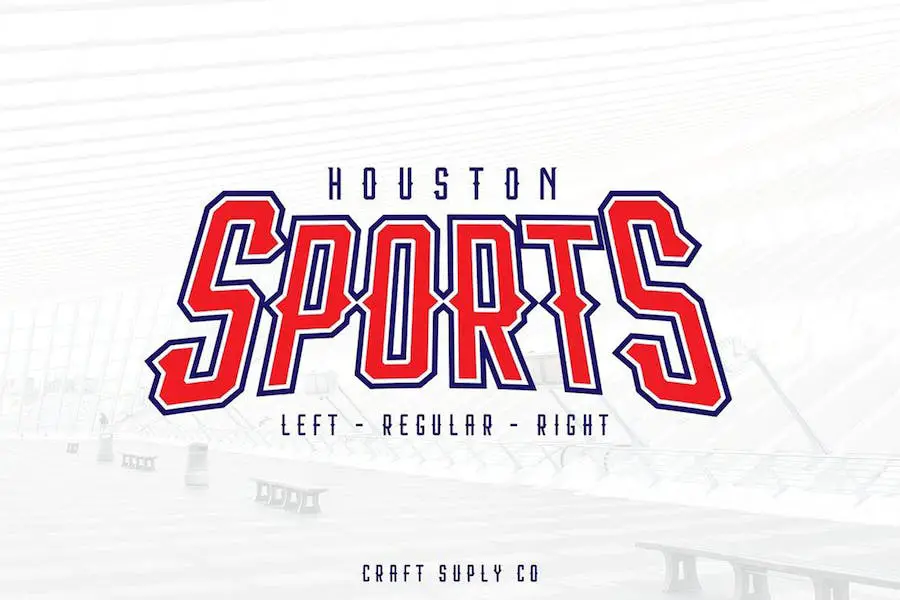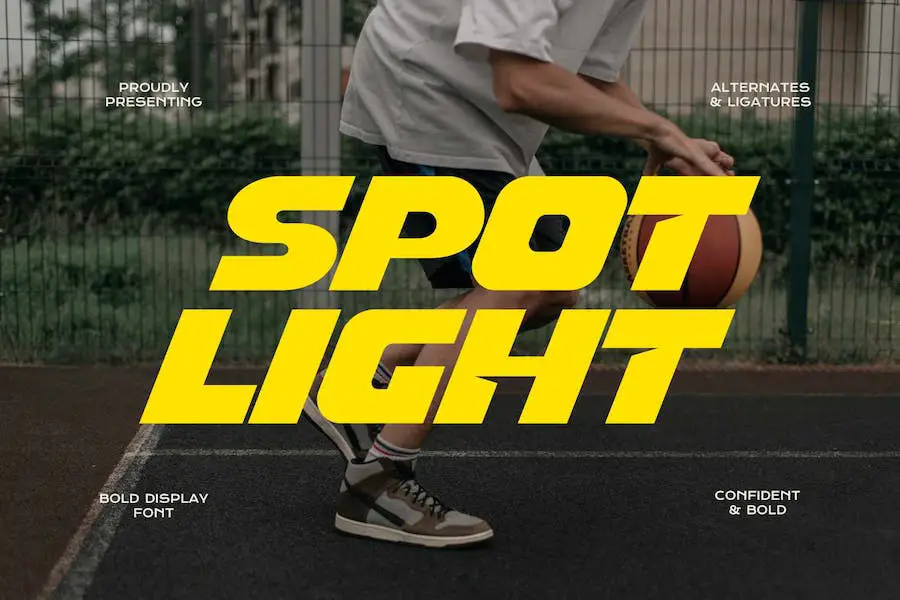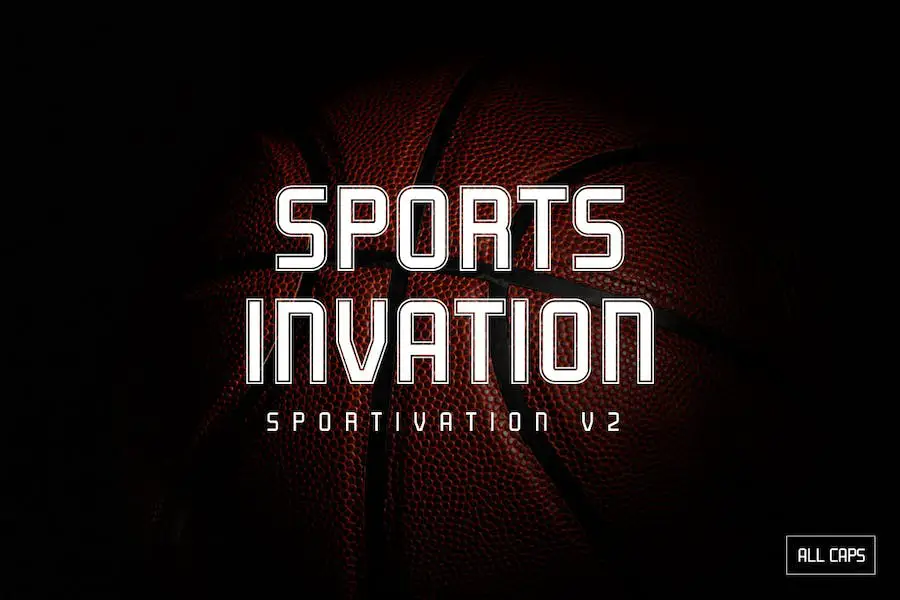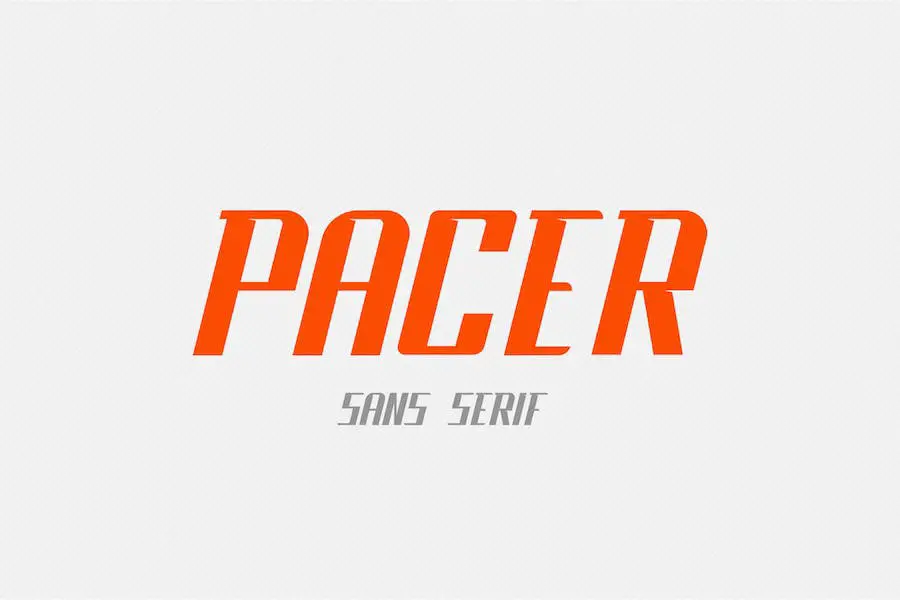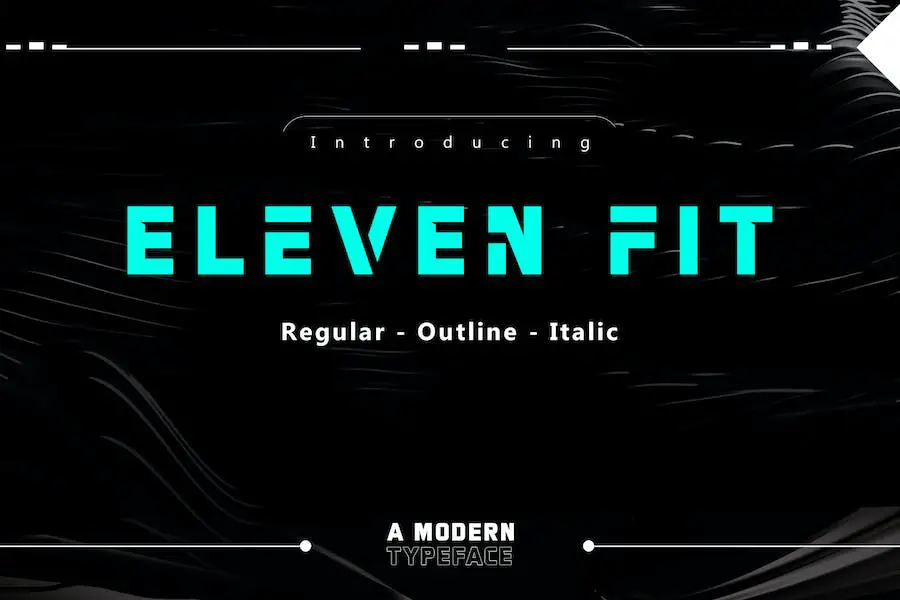
38 Font Olahraga Terbaik 2023 (Gratis & Premium)
Diterbitkan: 2023-07-16Apakah Anda seorang desainer grafis yang ingin membawa proyek Anda ke level selanjutnya? Apakah Anda lelah menggunakan font lama yang sama dan ingin menemukan sesuatu yang unik dan menarik? Nah, Anda beruntung!
Dalam posting blog ini, kami akan mengeksplorasi 38 font olahraga terbaik yang akan membantu meningkatkan permainan desain Anda dan membuat karya Anda menonjol.
Sekarang, Anda mungkin bertanya-tanya, “Mengapa font olahraga?” Nah, font olahraga adalah pilihan populer di kalangan desainer karena menghadirkan nuansa yang kuat dan dinamis pada desain apa pun.
Apakah Anda sedang mengerjakan proyek yang berhubungan dengan olahraga atau hanya ingin menambah energi dan kegembiraan pada desain Anda, font ini pasti akan berhasil.
Pada artikel ini, kami akan menampilkan berbagai macam font olahraga, mulai dari yang tebal dan atletis hingga ramping dan modern. Setiap font telah dipilih dengan cermat berdasarkan keunikan, keserbagunaan, dan kemampuannya untuk memberikan dampak visual.
Jadi apakah Anda sedang mendesain logo olahraga, poster, atau bahkan situs web, font-font ini akan membantu Anda membuat desain menakjubkan yang menangkap semangat olahraga.
Jadi, tanpa basa-basi lagi, mari selami dunia font olahraga dan temukan font terbaik yang akan membawa proyek desain Anda ke ketinggian baru.
Font Olahraga Premium Terbaik
Ingin membawa desain olahraga Anda ke level selanjutnya? Tidak terlihat lagi dari pilihan font premium terbaik kami yang dirancang khusus untuk proyek bertema olahraga. Bersiaplah untuk menyempurnakan desain Anda dengan tipografi terbaik ini yang pasti akan mengesankan audiens Anda.
Selami dan temukan font yang sempurna untuk proyek olahraga Anda berikutnya!
Olahraga Gimnasium
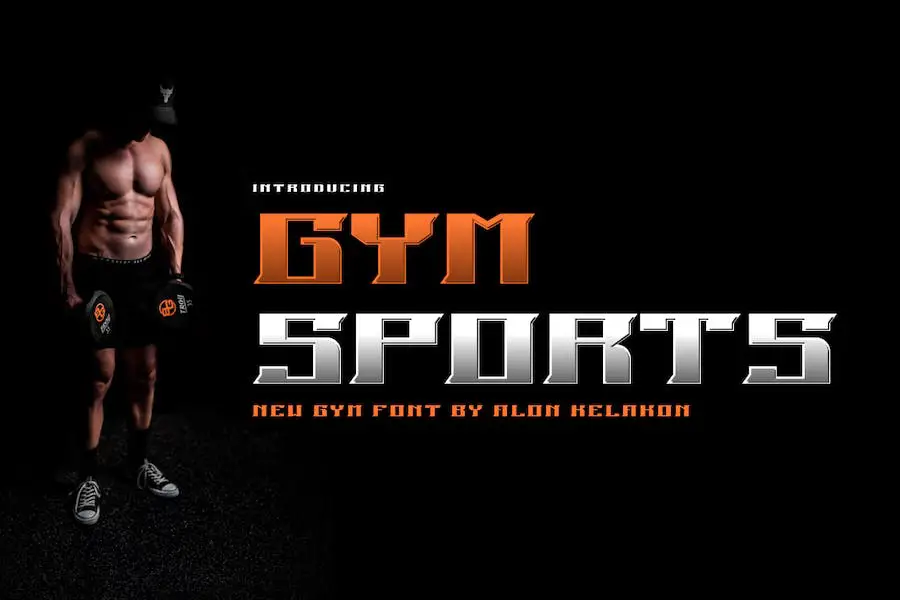
Gym Sports Font adalah jenis huruf unik dan serbaguna yang dapat meningkatkan proyek desain grafis Anda. Baik Anda membuat label, desain pakaian, poster film, atau logo, font ini siap membantu Anda.
Dengan tampilannya yang stylish dan dinamis, sempurna untuk menyampaikan rasa atletis dan energik. Gunakan Gym Sports Font untuk menambahkan sentuhan profesional dan menarik pada desain Anda.
Gym Sports Font juga merupakan pilihan tepat untuk judul film dan sampul album. Penampilannya yang berani dan dinamis menambahkan elemen yang menawan dan menarik secara visual pada produksi sinematik atau musik apa pun.
Grasher
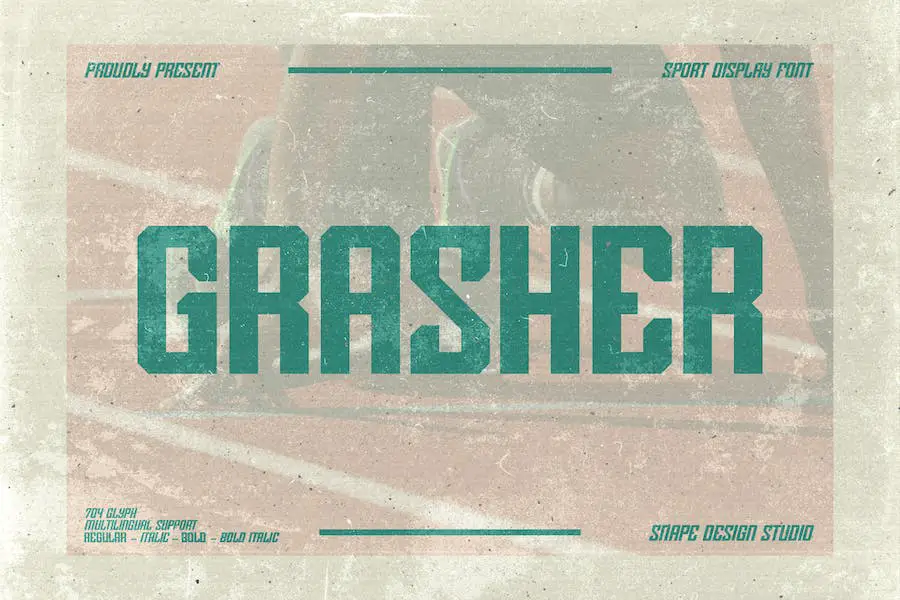
Grasher adalah font olahraga yang sempurna untuk logo, branding, dan desain atletik. Dengan rasa yang berani dan kuat, itu langsung menarik perhatian dan menambahkan sentuhan hidup pada proyek apa pun.
Baik Anda mendesain untuk tim olahraga, membuat poster atau sampul buku, atau bahkan mengerjakan film atau dokumenter, Grasher akan membuat desain Anda menonjol dengan gayanya yang unik.
Jika Anda penggemar estetika olahraga vintage, Grasher adalah font untuk Anda. Desainnya menangkap esensi tipografi olahraga klasik, memberikan desain Anda nuansa nostalgia dan autentik.
Ini sempurna untuk membuat logo, branding, atau desain yang terinspirasi gaya vintage yang membutuhkan sentuhan pesona olahraga jadul.
Berani
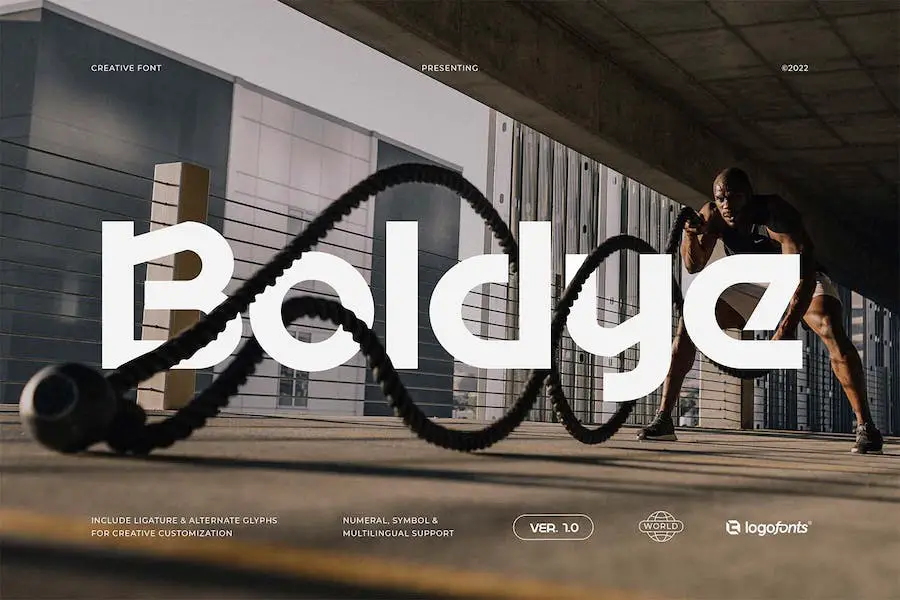
Memperkenalkan Boldye, font olahraga yang mengambil inspirasi dari logo ikonik Reebok dan gaya tipografi olahraga. Font ini adalah tentang kekuatan dan keserbagunaan, dengan kurva tebal dan tepi tajam yang memberikan desain Anda tampilan yang kuat dan dinamis.
Salah satu fitur menonjol dari Boldye adalah berbagai huruf dan pengikat alternatif uniknya, yang dapat diakses melalui fitur Open Type-nya.
Ini memungkinkan Anda dengan mudah membuat jenis logo Anda sendiri dan menambahkan sentuhan pribadi pada desain Anda. Dengan font ini, Anda benar-benar dapat melepaskan kreativitas Anda dan mewujudkan ide-ide Anda.
Olah Raga
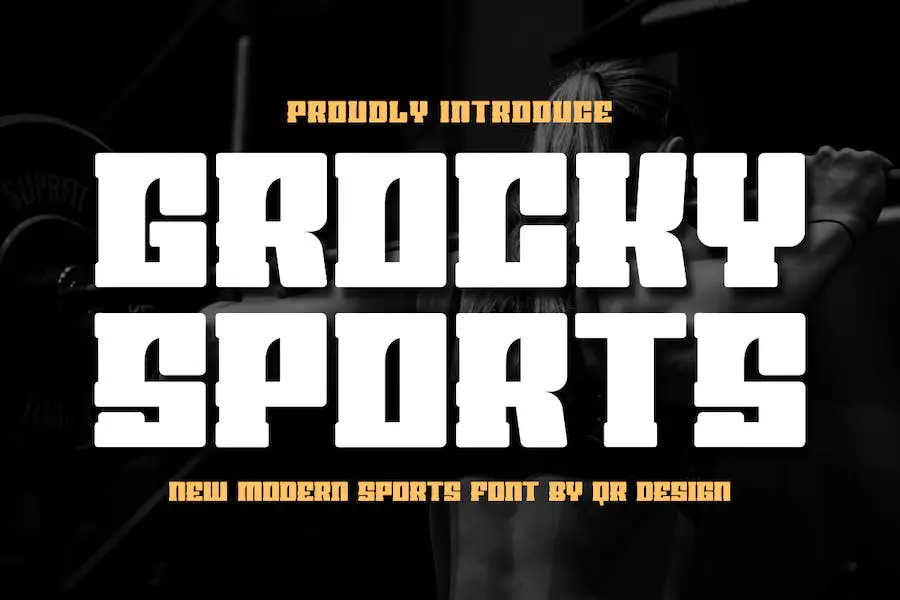
Grocky Sports adalah font olahraga unik yang sempurna untuk desainer grafis yang ingin menyempurnakan proyek mereka. Font ini serbaguna dan dapat digunakan untuk berbagai keperluan desain seperti pelabelan, pakaian, adegan film, poster, sampul album, logo, dan lainnya.
Desainnya yang modern dan bergaya akan menambah sentuhan profesional pada proyek apa pun. Dengan Grocky Sports, Anda dapat dengan mudah membuat desain menarik yang akan membuat klien Anda terkesan dan memikat audiens Anda.
Jadi mengapa puas dengan font biasa ketika Anda dapat meningkatkan desain Anda dengan font olahraga yang luar biasa ini? Coba Grocky Sports hari ini dan bawa proyek Anda ke level selanjutnya.
Heisman
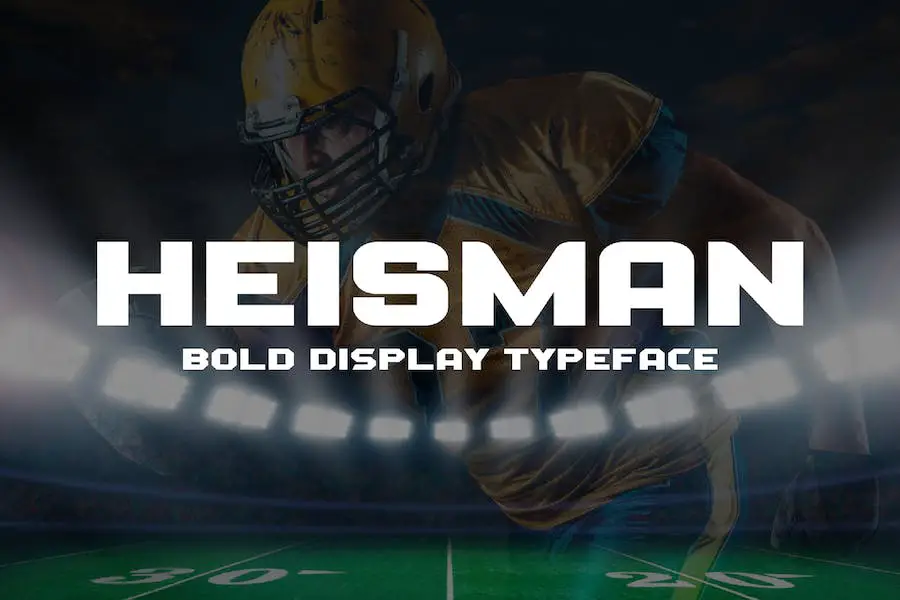
Heisman adalah pilihan utama bagi mereka yang berada di dunia desain grafis yang mencari font yang akan membawa proyek olahraga mereka ke level berikutnya.
Font huruf kapital semua ini menonjolkan kumpulan karakter huruf kecil dan besar yang unik, menjadikannya sempurna untuk iklan, tajuk utama, kaus, logo, branding, poster, pengemasan, dan banyak lagi.
Kesempurnaan geometrisnya menambah sentuhan estetis pada desain apa pun, sementara sifatnya yang sepenuhnya kern memastikan penggunaan yang mudah.